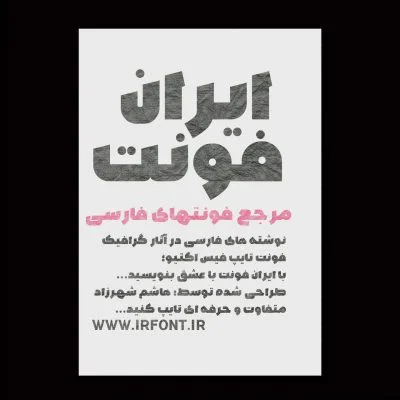
فونت شهرزاد
فونت فارسی شهرزاد
فونت فارسی شهرزاد که توسط جناب هاشم شهرزاد طراحی و اجرا شده است با ساختار ساده که به واسطه درست بکار رفتن این عناصر بسیار یکدست و زیبا خروجی می دهد این فونت خاص فارسی مناسب طراحی است و جزو فونت های فارسی و مناسب تایپوگرافی و نوشته های طولانی دسته بندی می شود. این فونت تنها در سایت ایران فونت و پس از پرداخت هزینه آن قابل تهیه است. هر گونه انتشار این فونت در سایت های دیگر خلاف قانون و پیگرد قانونی دارد. از اهتمام کاربران در تهیه این فونت تنها از طریق سایت ایران فونت سپاس گزاریم.